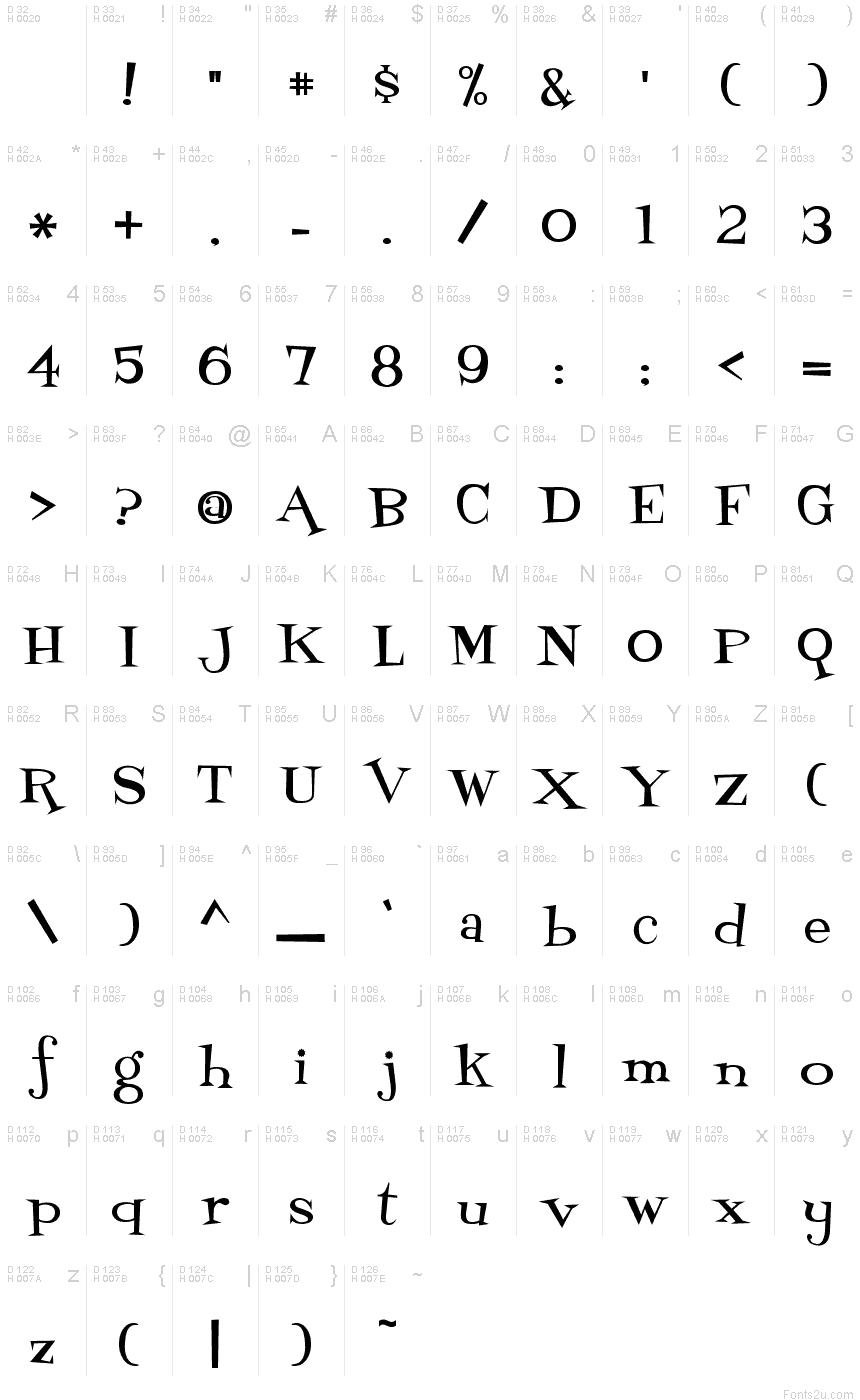
Fontdinerdotcom Loungy
Die Fontdinerdotcom Loungy von Font Diner ist eine kostenlose, retro-inspirierte Comic-Serifenschrift, die wirkt, als käme sie direkt von der schicken Cocktailkarte einer Bar aus der Mitte des letzten Jahrhunderts. Die hohen, leicht schiefen Buchstaben in lässigen Winkeln, kombiniert mit keilartigen Serifen und ungleichmäßigen, tuscheartigen Strichen, verleihen jedem Wort eine beschwipste Lounge-Attitüde. Sie ist fett, eigenwillig und ein wenig theatralisch – perfekt für Schlagzeilen, die den Star des Abends ankündigen.
Mit Fontdinerdotcom Loungy bekommen Ihre Titel sofort diesen kitschigen Vintage-Club-Vibe, der auf Postern, Tiki-Bar-Menüs, Partyeinladungen, Retro-Brandings, Verpackungen und verspielten Schildern glänzt. Diese kostenlose Schrift liebt große Formate, bei denen ihr kecker Schwung und ihre kräftigen Formen voll zur Geltung kommen. Für den Fließtext empfiehlt es sich, eine klare, dezente serifenlose Schrift zu wählen, damit der exzentrische Charme der Loungy voll im Rampenlicht steht.